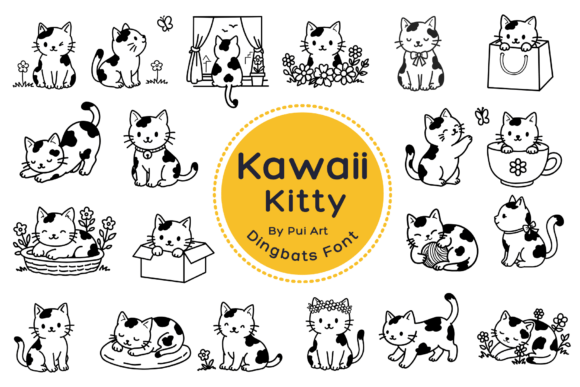
Kawaii Kitty Doodle
適切なデザイン要素を見つけるのは難しい場合がありますが、Kawaii Kitty Doodleは作品を即座に引き立てる優れたコレクションを提供します。
POD(オンデマンド印刷)製品、結婚式の招待状、またはソーシャルメディアのグラフィックを作成している場合でも、Kawaii Kitty Doodleは理想的です。